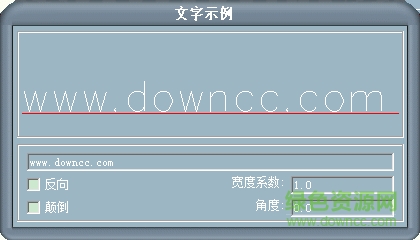
qz.shx
qz.shx是針對(duì)autocad軟件設(shè)計(jì)的一款字體,該字體樣式簡(jiǎn)單易讀性強(qiáng),擁有完整豐富的字體,兼容AutoCAD的各個(gè)版本及Windows的所有系統(tǒng),安裝方法簡(jiǎn)單,需要的朋友歡迎來(lái)綠色資源網(wǎng)下載!
qz.shx字體簡(jiǎn)介
qz.shx字體